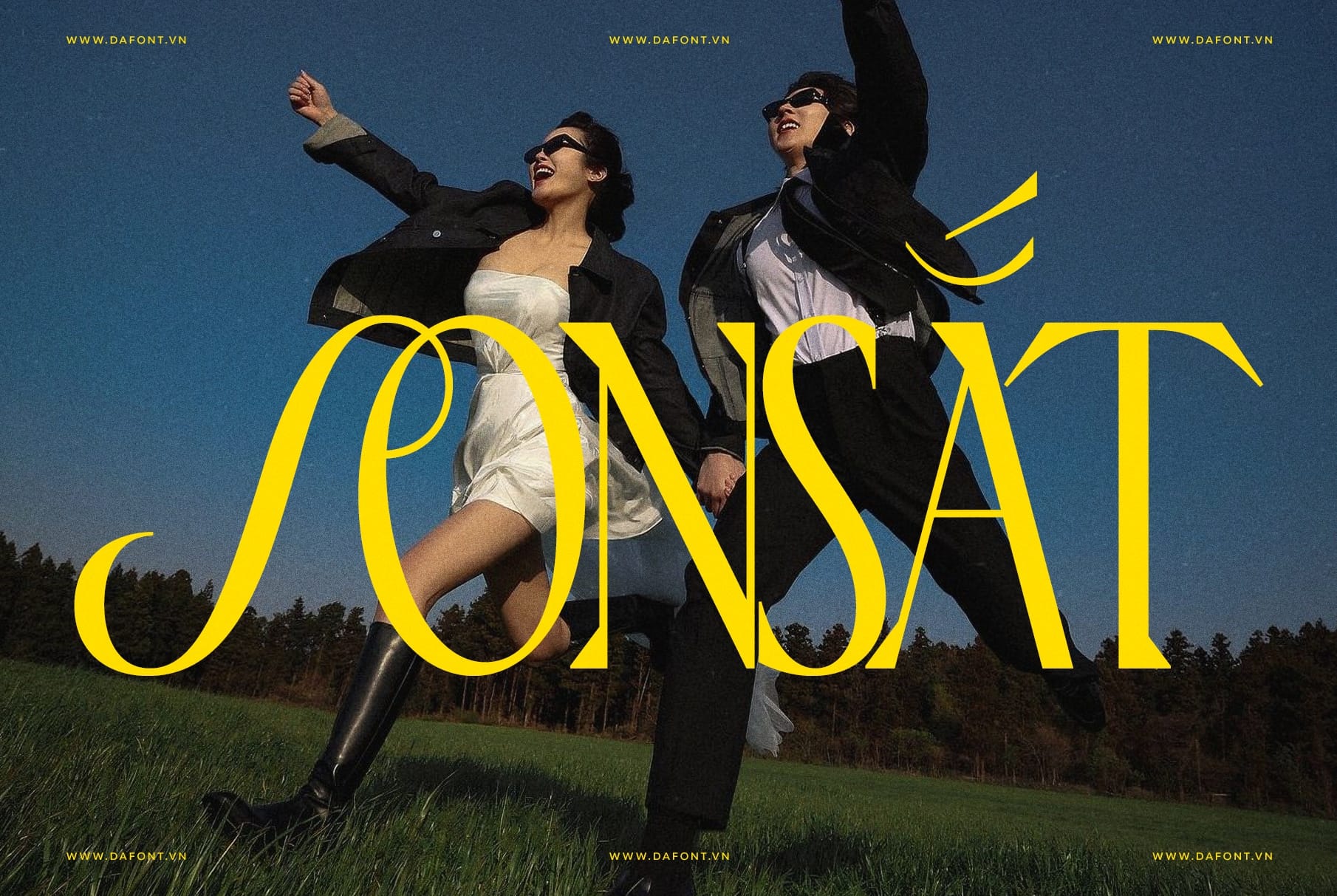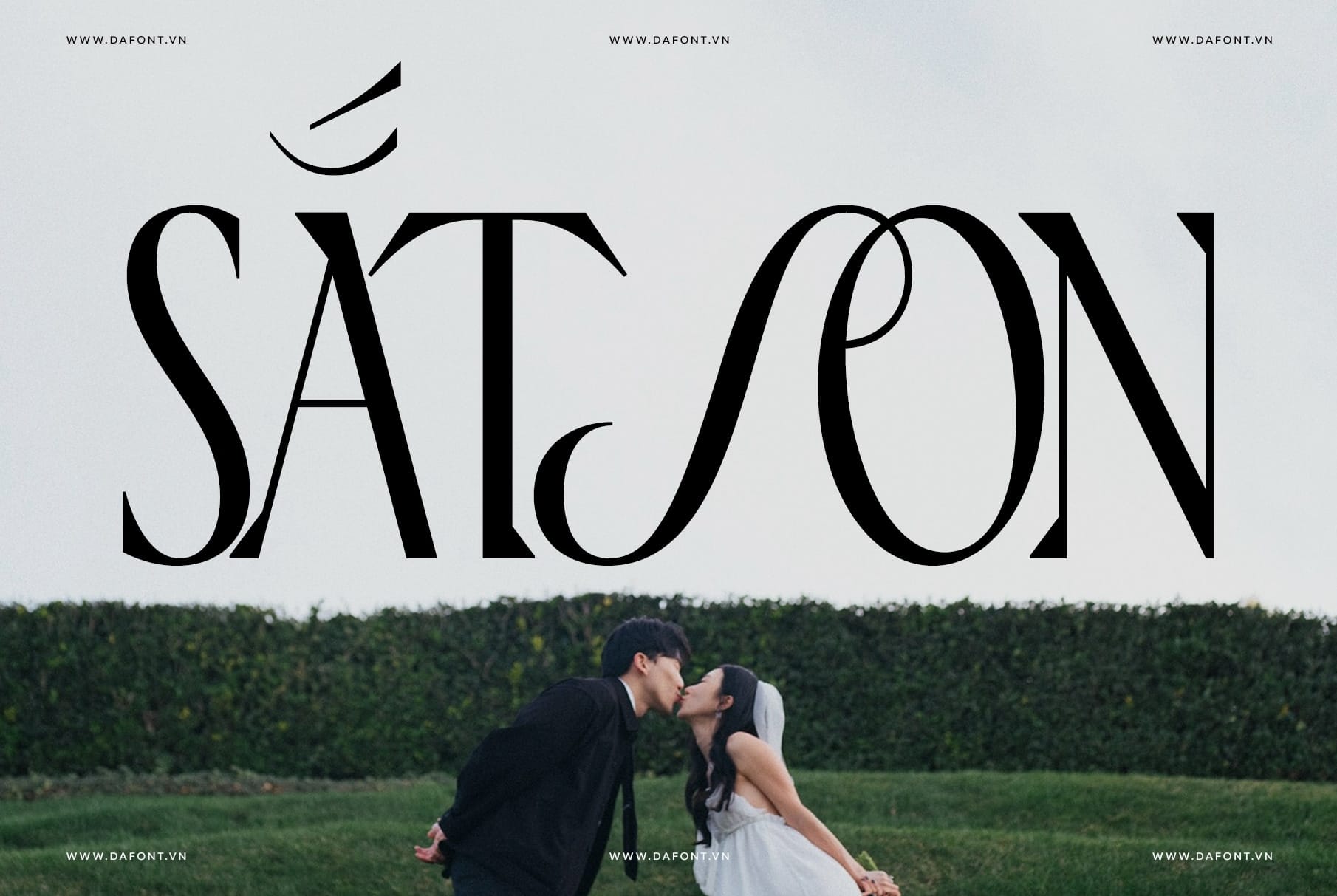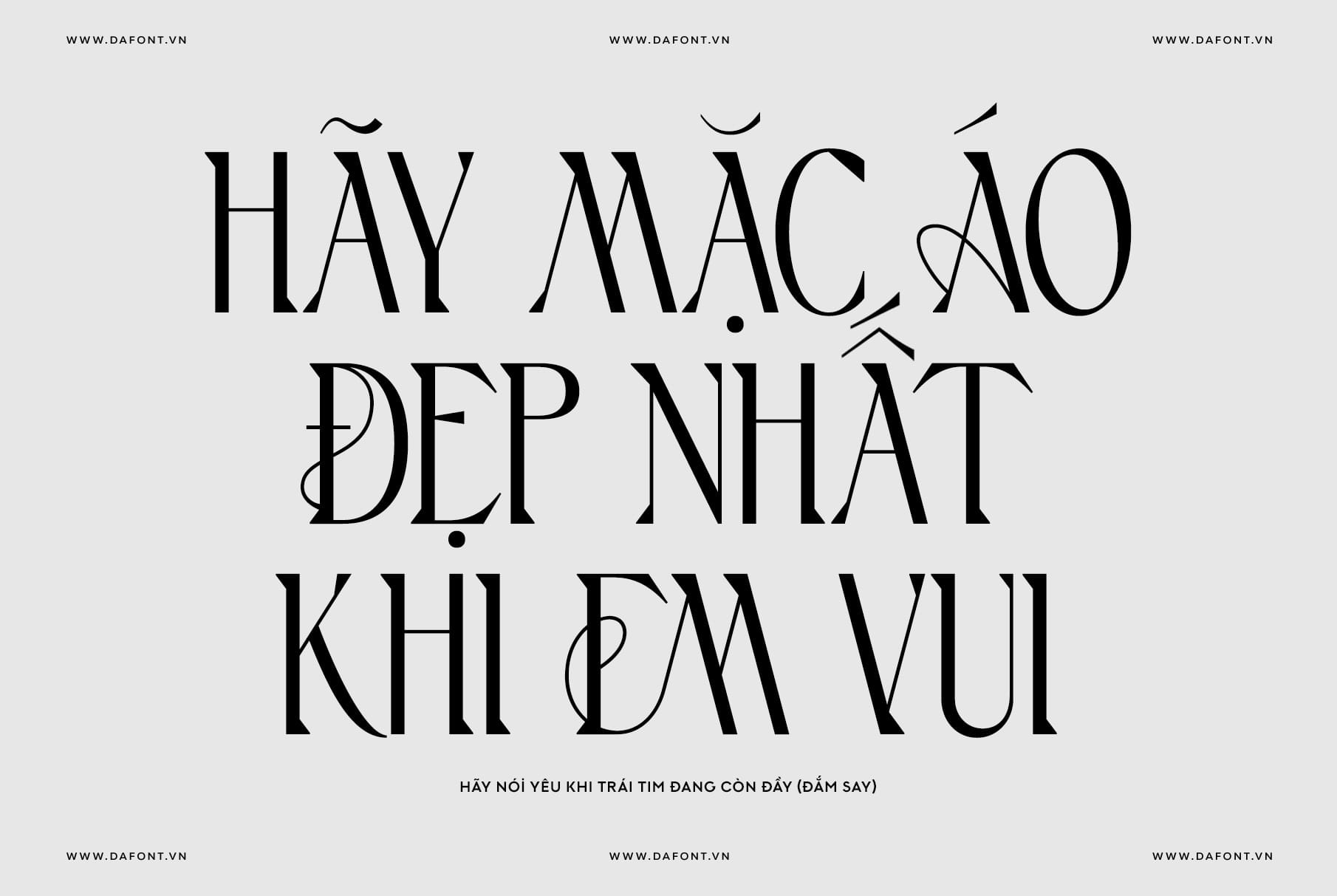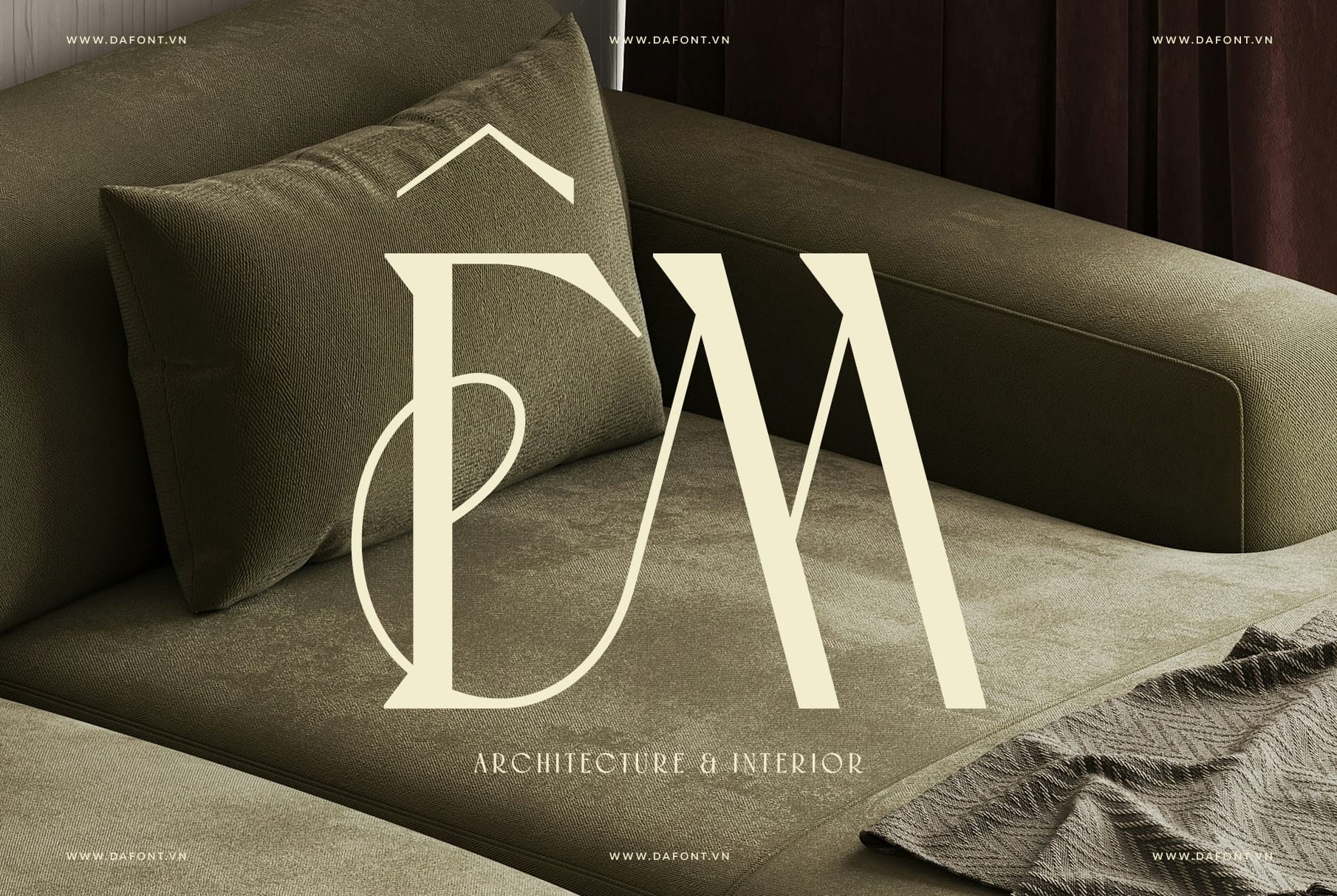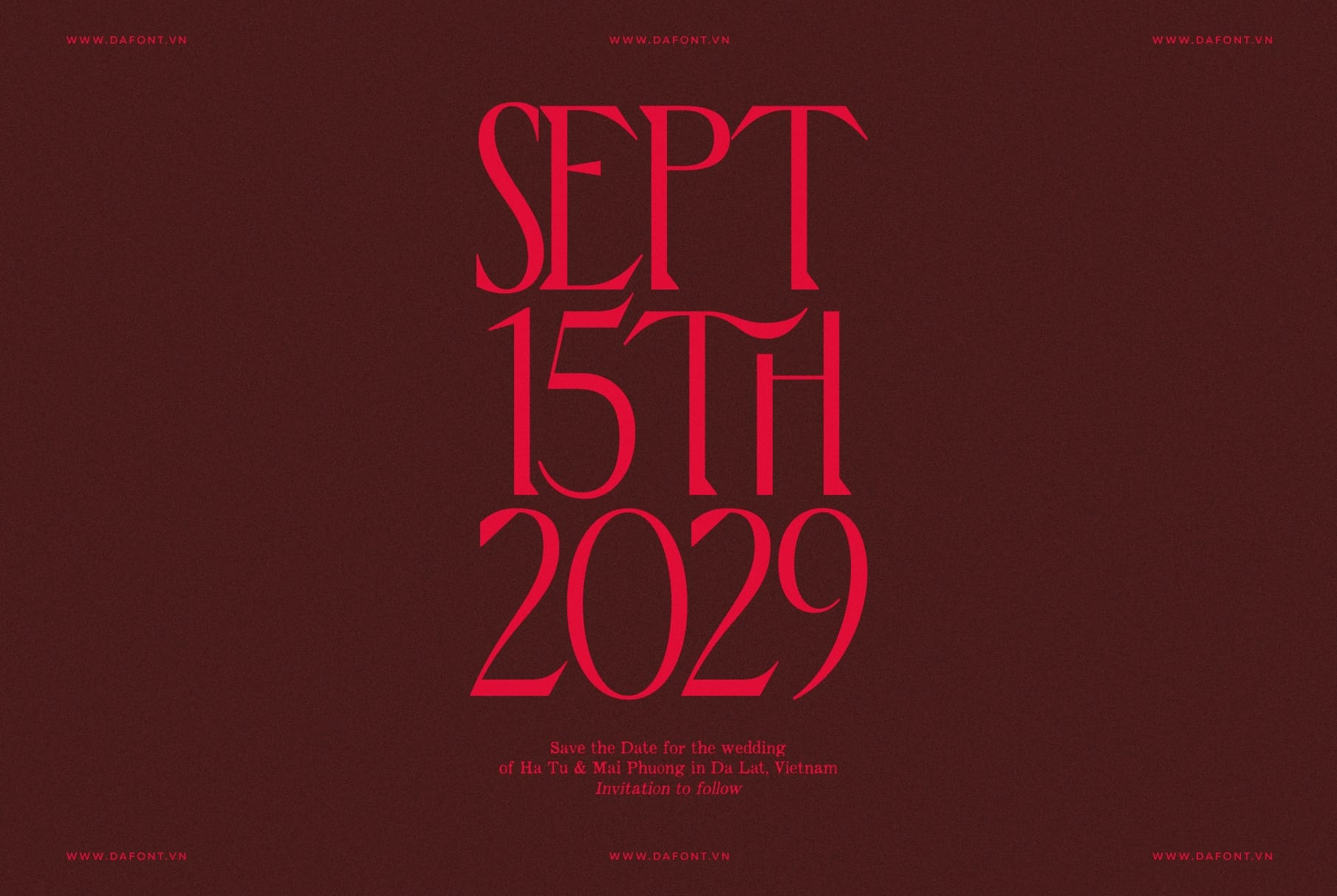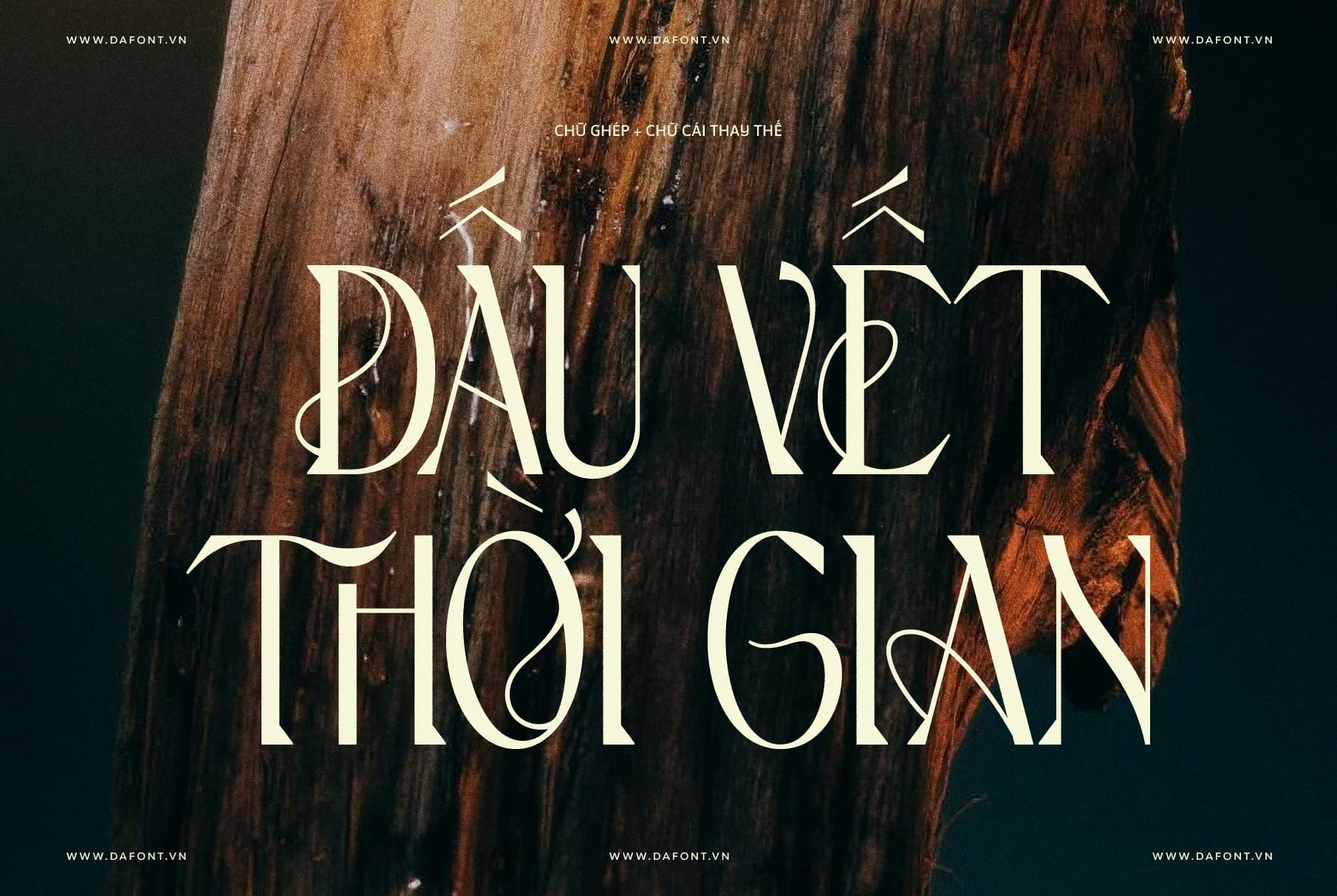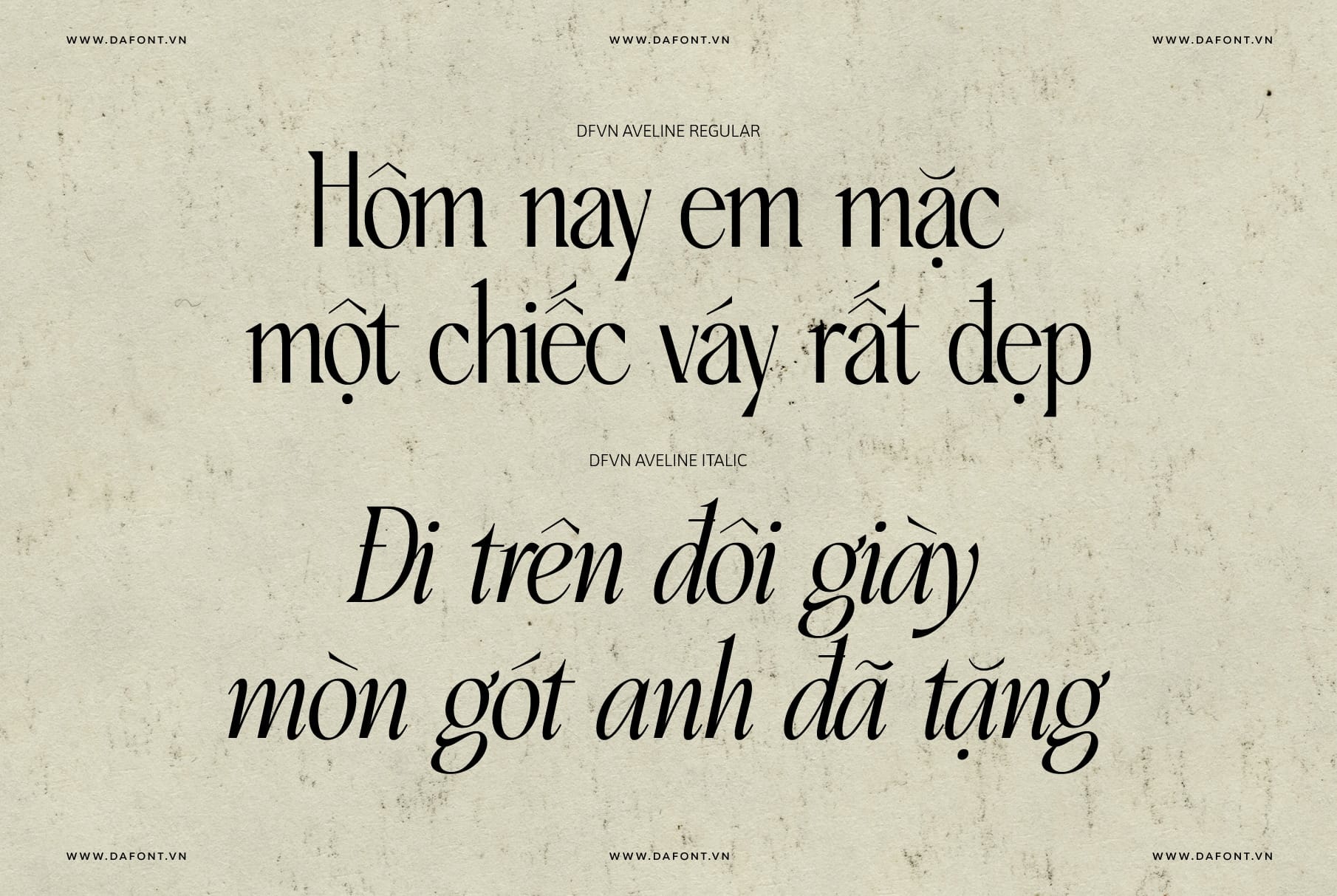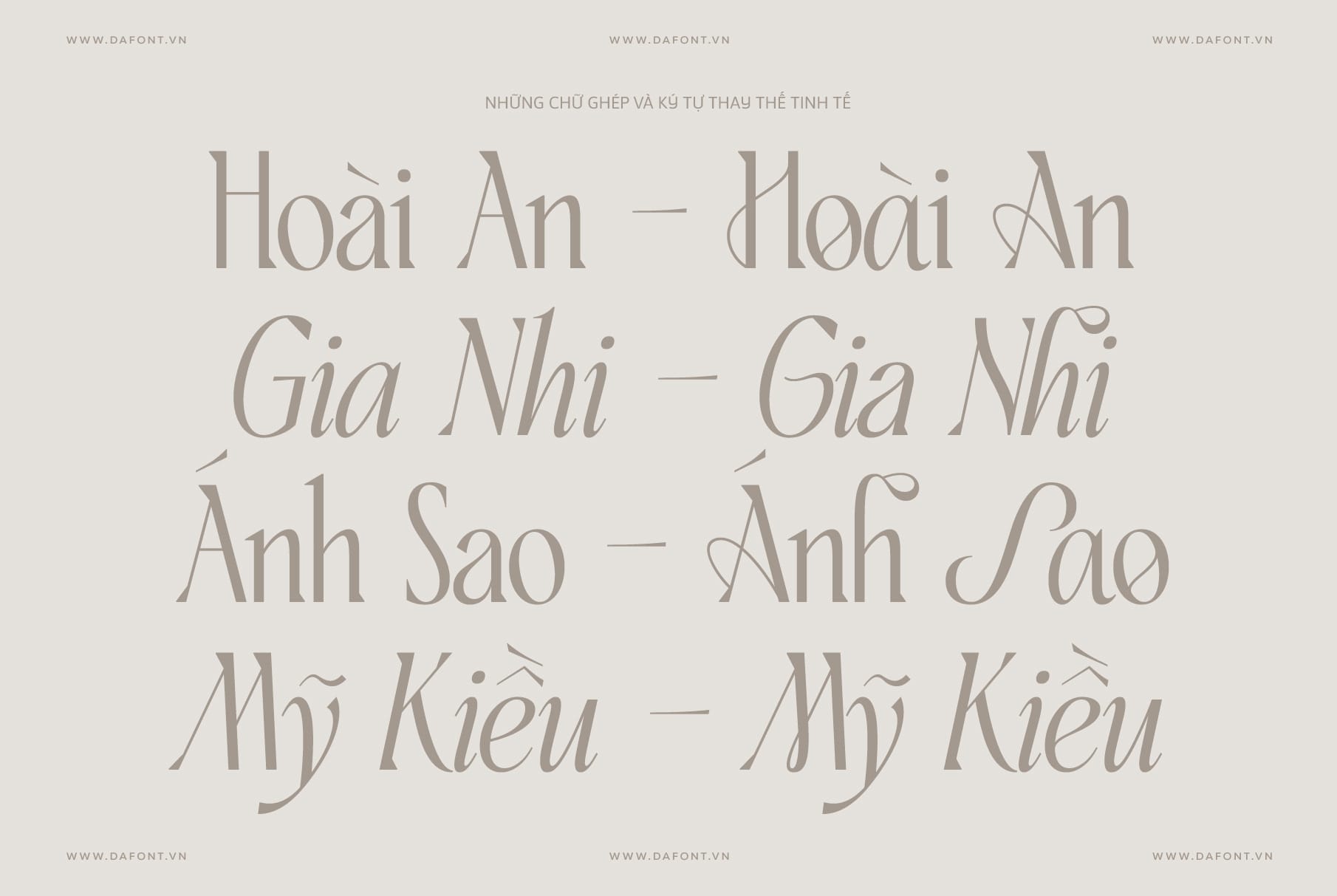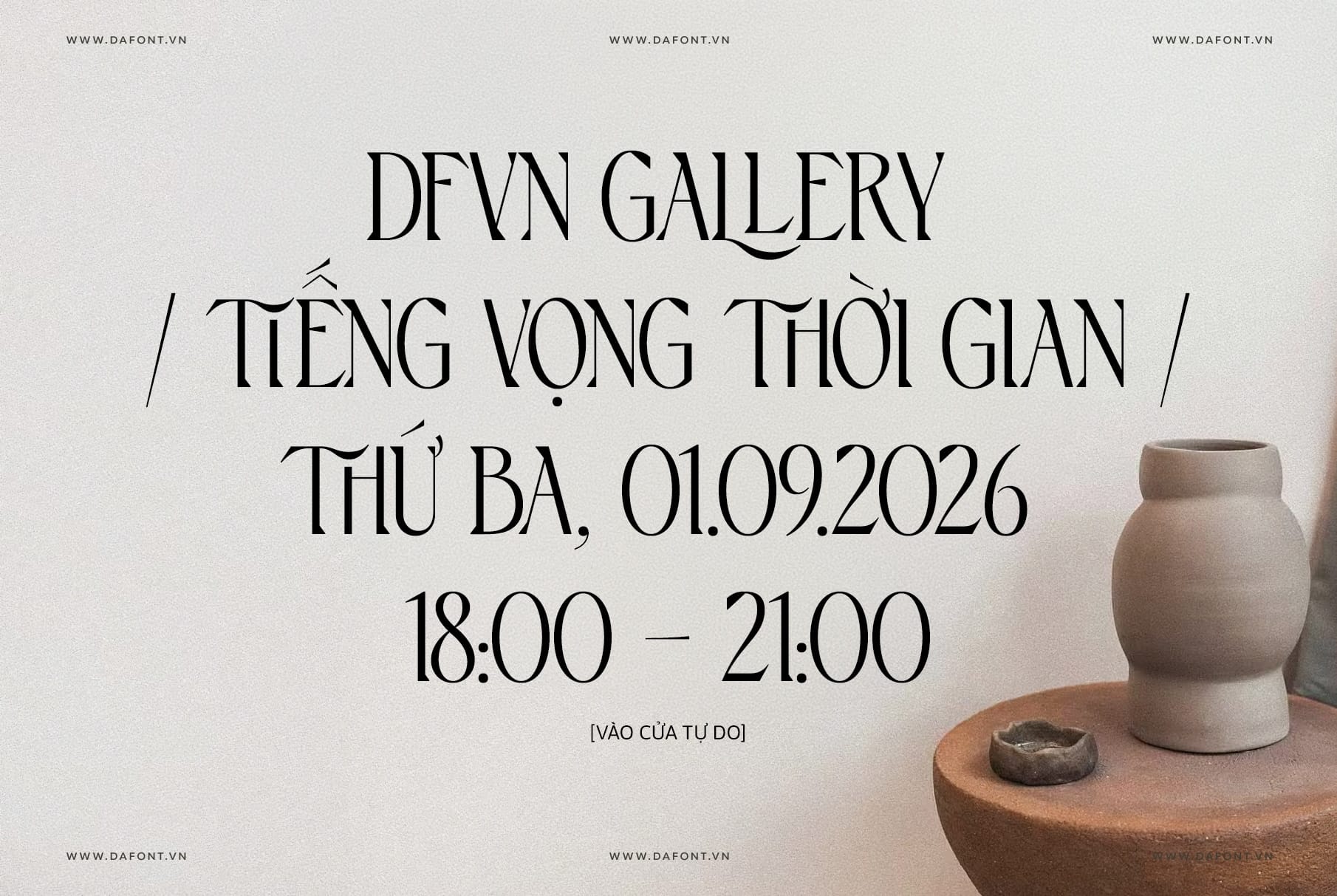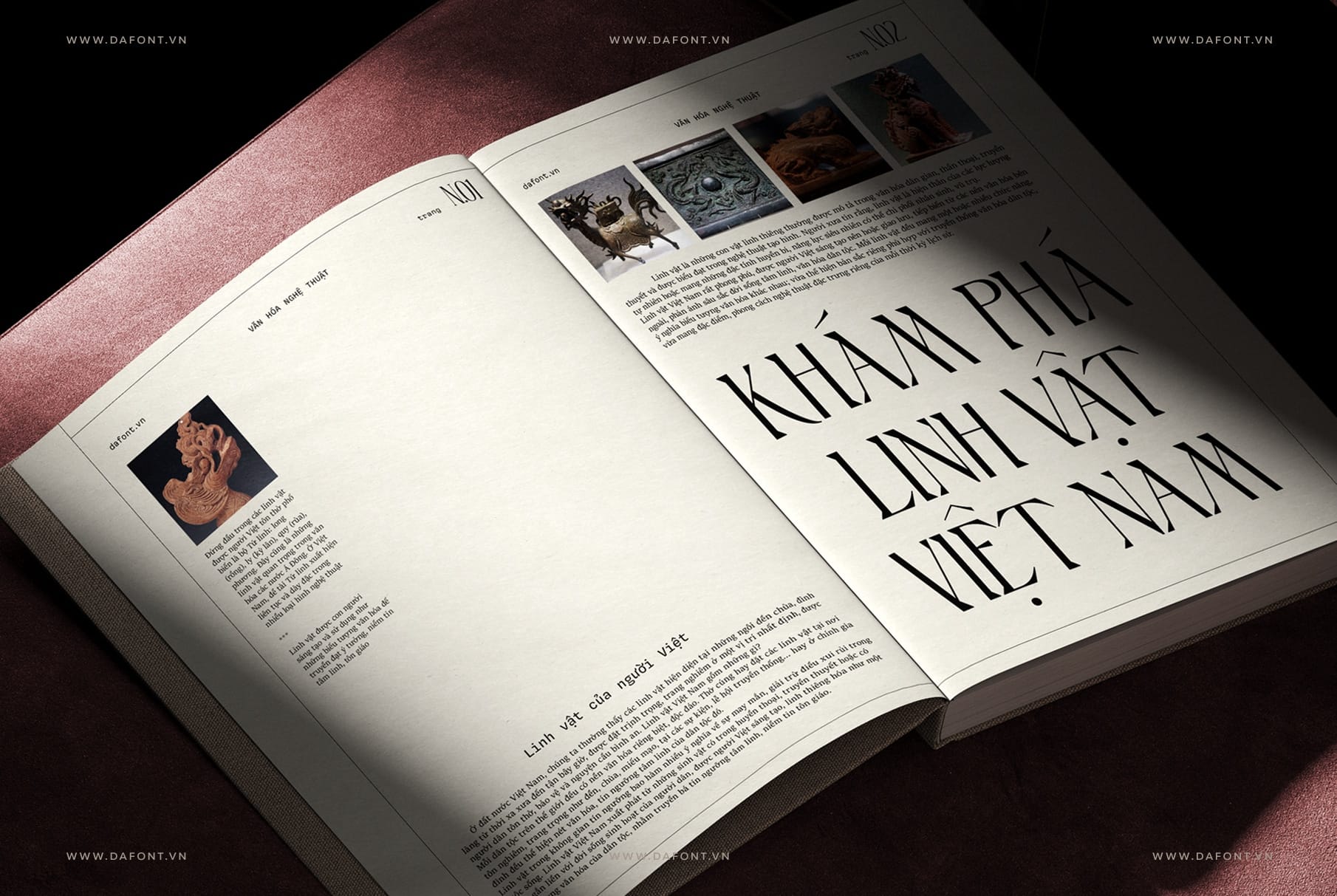
Nếu bạn đang tìm kiếm một kiểu chữ giao thoa hoàn hảo giữa vẻ đẹp cổ điển và sự tối giản hiện đại, thì Aveline chính là chân ái. Vượt ra khỏi những quy chuẩn cứng nhắc của font serif truyền thống, DFVN Aveline mang đến một luồng gió mới, thanh lịch và vô cùng linh hoạt cho mọi dự án đồ họa.
Đặc điểm nổi bật của font DFVN Aveline
Điểm đặc biệt nhất của Aveline nằm ở sự kết hợp giữa form chữ mềm mại và bao gồm các chữ ghép và ký tự thay thế cực kỳ phong phú. Các chữ ghép được vẽ riêng giúp từng từ trông như một wordmark được thiết kế thủ công chứ không chỉ là text gõ thông thường.
- Kiểu chữ lai giữa serif và sans: Cấu trúc chữ mang tinh thần hiện đại với bộ khung rõ ràng, kết hợp cùng các chân serif mềm mại, tạo nên tổng thể thanh lịch và cao cấp.
- Font có tỷ lệ cân đối, độ tương phản nét vừa phải, giúp giữ được sự rõ ràng và ổn định ngay cả khi sử dụng ở kích thước nhỏ.
- Số lượng lớn ligature và ký tự thay thế giúp việc dàn chữ trở nên linh hoạt hơn, đồng thời tạo ra những heading hoặc wordmark mang dấu ấn riêng.
- Font bao gồm Roman và Italic, hỗ trợ đa ngôn ngữ, đầy đủ dấu câu, chữ số và các tính năng OpenType phục vụ tốt cho nhu cầu thiết kế chuyên nghiệp.
Tổng thể, DFVN Aveline mang đến cảm giác mềm mại, tinh tế và sang trọng một cách tiết chế. Đây là kiểu chữ đặc biệt phù hợp với những thương hiệu theo đuổi hình ảnh thanh lịch, hiện đại và giàu tính thẩm mỹ, đặc biệt trong lĩnh vực thời trang, làm đẹp và editorial.
Ứng dụng thiết kế hoàn hảo
Nhờ sự cân bằng giữa tính hiện đại và nét duyên dáng, DFVN Aveline có thể thích ứng linh hoạt trong nhiều hạng mục thiết kế khác nhau:
- Nhận diện thương hiệu & Bao bì (Branding & Packaging): Rất lý tưởng cho thiết kế Logo, hệ thống nhận diện hình ảnh của các thương hiệu làm đẹp (spa, mỹ phẩm, thời trang) hoặc bao bì sản phẩm cao cấp cần sự thanh lịch.
- Ấn phẩm & Editorial: Trở nên cực kỳ thu hút khi dàn trang biên tập (editorial layout), thiết kế bìa tạp chí, lookbook, bìa sách hoặc làm thư mời, thiệp cưới cao cấp.
- Mạng xã hội & Digital: Làm nổi bật các đoạn tiêu đề (headline), thiết kế typography cho quotes, banner website hoặc các chiến dịch truyền thông yêu cầu sự mềm mại, tinh tế.
Tổng Kết
DFVN Aveline Việt hóa gây ấn tượng bởi cấu trúc chữ được thiết kế khéo léo, kết hợp giữa nét thanh lịch của serif và cảm giác mềm mại, hiện đại trong tổng thể. Đi cùng với đó là hệ ligatures phong phú, giúp từng dòng chữ trở nên uyển chuyển, liền mạch và giàu tính thẩm mỹ hơn khi đưa vào thiết kế.
Đây không chỉ là một kiểu chữ đẹp để sử dụng trong những bố cục thông thường, mà còn là lựa chọn rất đáng giá cho những ai muốn khai thác typography như một điểm nhấn thị giác thực thụ. Từ branding, editorial, bao bì cho đến các ấn phẩm mang phong cách tinh tế, DFVN Aveline Việt hóa đều có khả năng mang lại cảm giác chỉn chu, sang trọng và cuốn hút hơn cho tổng thể. Nếu bạn đang muốn bổ sung một font serif vừa mềm mại, nhẹ nhàng vừa có chiều sâu vào bộ sưu tập của mình, đây chắc chắn là cái tên rất đáng để cân nhắc.